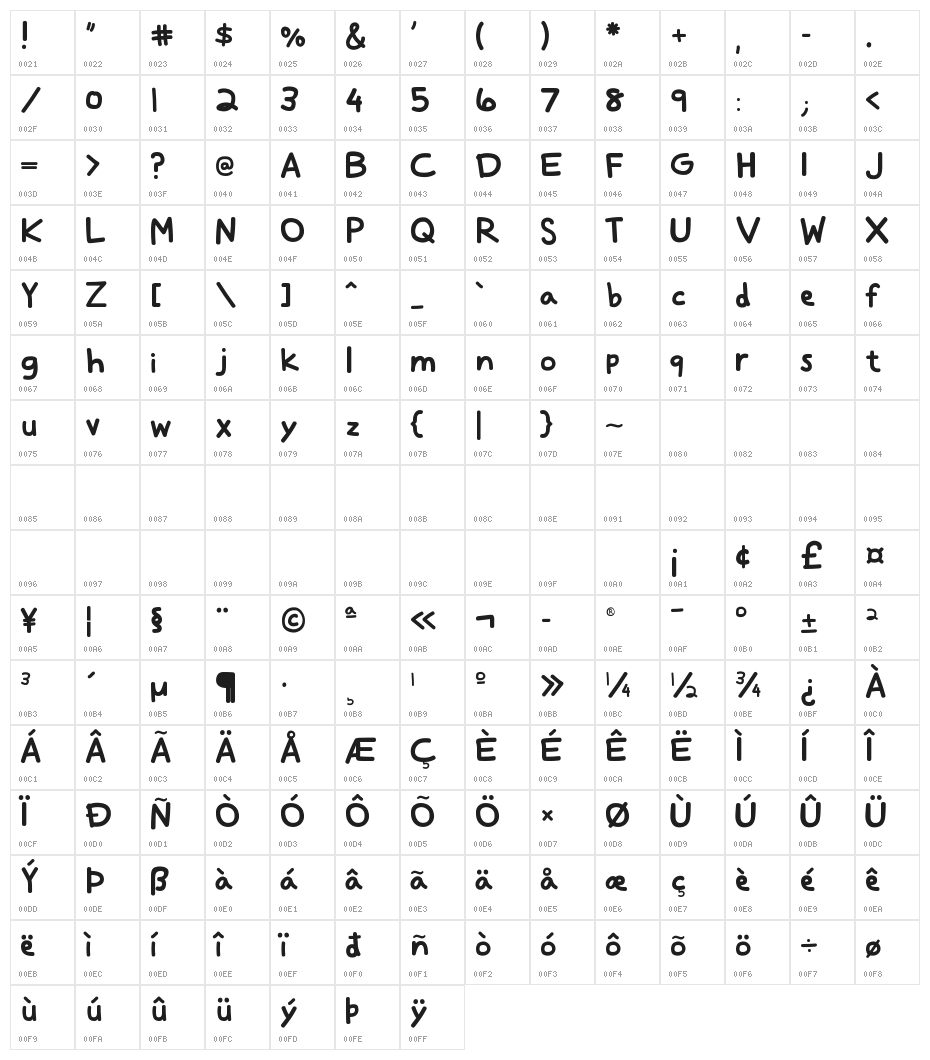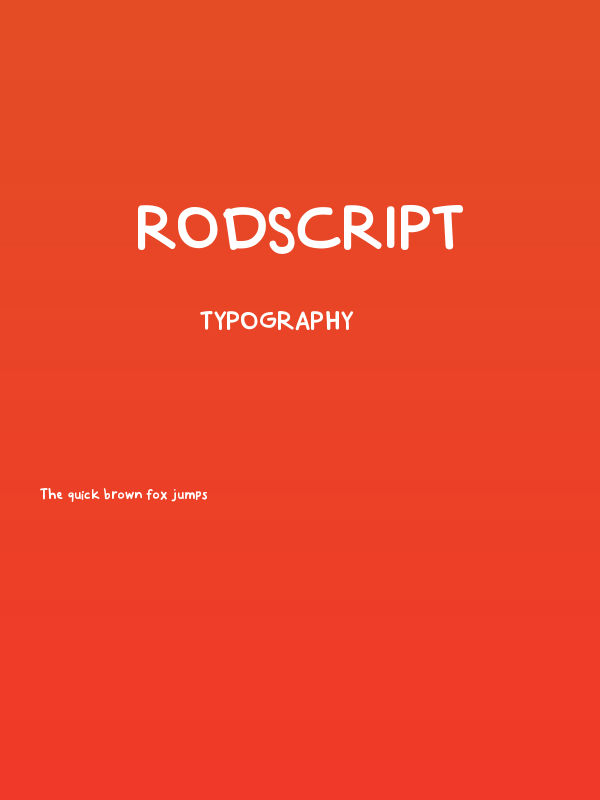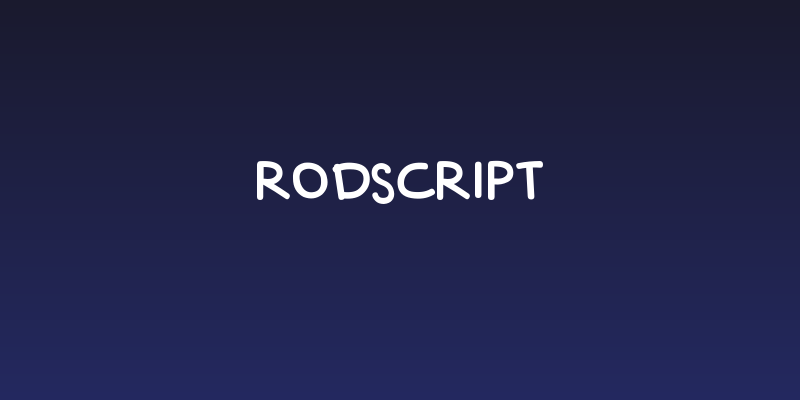
Rodscript Font
| 用途 | Headlines, Logos, Informal Text |
| おすすめプロジェクト | Ideal for children's books, playful branding, casual invitations, and creative posters. |